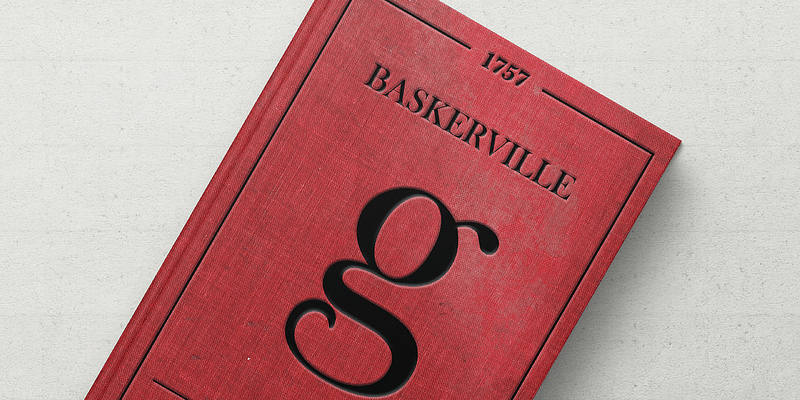
John Baskerville は究極の書体を作るために努力を惜しみませんでした。彼は、生涯にわたって習得したカリグラフィーと石切りの知識に基づいて、深い黒のインクと滑らかな紙を使って、John Handy に自身の素晴らしいデザインからカットしてもらった文字を最大限に効果的に見せるようにしました。パンチと母型はケンブリッジ大学出版局に残っています。現在の書体は、1929 年に Linotype & Machinery Ltd のために Baskerville の英語 (14pt) のローマン体とイタリック体の組版を基にして George W. Jones が細心の注意を払って作り直した正確な再カット版です。この年は、Mergenthaler Linotype がこの書体を米国に輸入した 2 年後のことでした。